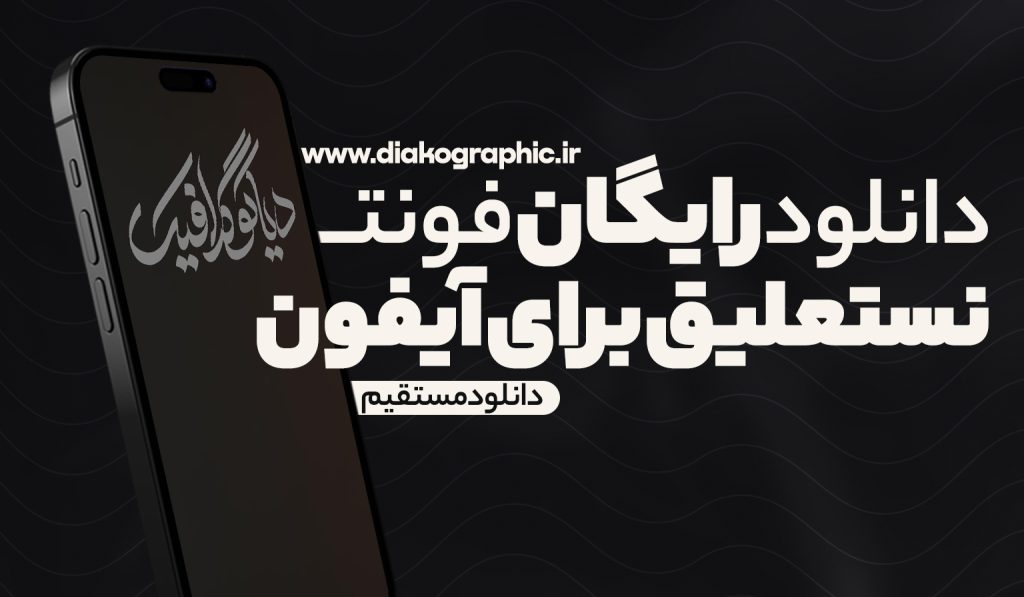
یکی از مهمترین مؤلفههای تولید محتوای فارسی، مخصوصاً در آیفون، انتخاب فونت مناسب است. اگر تا حالا به این فکر کردید که چطور میشود از فونت نستعلیق، این شاهکار خوشنویسی ایرانی، روی گوشی آیفون استفاده کرد، جای درستی آمدید! در این مطلب از سایت دیاکوگرافیک قصد داریم یک راهنمای کامل برای دانلود رایگان فونت نستعلیق آیفون ارائه بدهیم. فونتی که نهتنها زیبایی بصری فوقالعادهای داره، بلکه حس اصالت و فرهنگ ایرانی رو به محتوای دیجیتال تو تزریق میکنه.
چه طراح گرافیکی باشی، چه تولیدکننده محتوا، یا حتی کسی که صرفاً دوست دارد پیامهای خاصتری در استوری یا شبکههای اجتماعی بذارد، فونت نستعلیق میتواند ابزار قدرتمند تو باشد. برای دانلود رایگان فونت نستعلیق آیفون به ادامه مطلب مراجعه کنید.
چرا فونت نستعلیق در آیفون اهمیت دارد؟
شاید اولین سوال این باشد که «اصلاً چرا باید فونت نستعلیق را روی آیفون نصب کنیم؟». پاسخ سادهست: چون فونتهای پیشفرض آیفون برای فارسینویسی نه تنها زیبایی ندارن، بلکه گاهی خوانایی پایینی هم دارند. فونت نستعلیق یکی از نمادهای تاریخی و هنری فارسی است. این فونت به نوشتهها جلوهای شاعرانه، اصیل و متفاوت میدهد که فونتهای استاندارد فارسی در iOS اصلاً نمیتوانند ارائه بدهند.
مواردی که فونت نستعلیق را بیرقیب میکند:
- تلفیق خطاطی سنتی با ابزار دیجیتال
- مناسب برای پستها و استوریهای احساسی، مذهبی و رسمی
- بسیار کاربردی برای طراحی کارت تبریک، اعلامیه، پوستر، اسلاید و …
- کاربرد در برنامههای نوشتاری مثل Pages یا Keynote برای ایجاد فایلهای رسمی با هویت ایرانی
فرض کن یک کارت دعوت برای مراسم رسمی میخواهید طراحی کنید. اگر از فونت نستعلیق استفاده کنید، نوشتهت تبدیل میشود به یک اثر هنری.
اپلیکیشنهای محبوبی که با فونت نستعلیق هماهنگ هستند
| نام اپلیکیشن | قابلیت استفاده از فونت سفارشی | مناسب برای |
|---|---|---|
| Canva | بله | طراحی پست، استوری، بنر |
| Phonto | بله | افزودن متن نستعلیق روی عکس |
| Over | بله | طراحی حرفهای شبکههای اجتماعی |
| Pages | بله | تایپ حرفهای فارسی |
| Keynote | بله | ساخت اسلایدهای فارسی با استایل سنتی |
اگر تو یک کسبوکار محتوایی هستید و یا حتی تولیدکننده محتوای شخصی، استفاده از فونتهای سفارشی مثل نستعلیق باعث افزایش چشمگیر جذابیت بصری محتوایت میشود.
چرا فونت نستعلیق در شبکههای اجتماعی ترند شده؟
طراحان، بلاگرها، فعالان مذهبی، کسبوکارهای سنتی، همه دنبال فونتی هستند که حس خاصتری را به مخاطب القا کند. فونت نستعلیق دقیقاً همین کار را انجام میدهد. از طراحیهای مذهبی گرفته تا استوریهای عاشقانه، این فونت همیشه تأثیرگذار ظاهر میشود.
نکات مهم برای استفاده حرفهای از فونت نستعلیق در آیفون
- از فونت نستعلیق در متنهای بلند استفاده نکن؛ چون خوانایی پایین میاره.
- بهتره در عناوین، نقل قولها یا بخشهای کلیدی استفاده بشه.
- همیشه از نسخههای Unicode یا نسخههای سبکشده استفاده کن برای کیفیت بهتر.
- در طراحیهایی با بکگراند تیره، فونت نستعلیق سفید یا طلایی جذابتره.
دنیایی که طراحی و هویت بصری نقش کلیدی در دیدهشدن دارند، استفاده از فونتهایی مثل نستعلیق میتونه محتوای فارسی رو به سطح بالاتری برسونه. فونت نستعلیق فقط یک انتخاب نیست؛ یک امضای هنریه. حالا که روش نصبش روی آیفون رو یاد گرفتی و فونتهای رایگان رو هم دانلود کردی، وقتشه متفاوت بنویسی، خاص طراحی کنی و با هویت ایرانی بدرخشی.